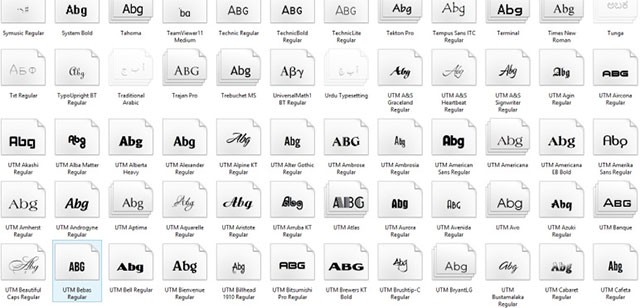
Khám Phá Bộ Font UTM: Giải Pháp Gõ Tiếng Việt Hoàn Hảo
Bộ font UTM, viết tắt của Unicode Thiên Minh, là một tập hợp các font chữ tiếng Việt sở hữu nhiều kiểu dáng độc đáo và ấn tượng.
Với tổng cộng 196 font UTM và 307 font SFU đã được Việt hóa, bộ font này tương thích hoàn toàn với bộ mã Unicode chuẩn.
Điều này đồng nghĩa với việc bạn có thể sử dụng bộ font UTM một cách an tâm trên các phần mềm gõ tiếng Việt phổ biến như Unikey hoặc Vietkey .
Việc tích hợp hoàn hảo với Unicode giúp đảm bảo khả năng hiển thị chính xác và nhất quán của văn bản tiếng Việt trên mọi nền tảng.
Bộ font UTM mang đến sự lựa chọn đa dạng về phong cách chữ, đáp ứng nhu cầu sáng tạo và trình bày văn bản của người dùng.
Tính năng nổi bật của Bộ font UTM
Bộ font UTM được xây dựng để tương thích hoàn toàn với bảng mã Unicode, đảm bảo việc hiển thị và nhập liệu tiếng Việt diễn ra chính xác, loại bỏ hoàn toàn các vấn đề liên quan đến font chữ. Sự tương thích này được kiểm chứng trên các phần mềm gõ tiếng Việt thông dụng như Unikey và Vietkey.
Sự phong phú về kiểu dáng là một điểm mạnh của bộ font này. Nó cung cấp nhiều lựa chọn về phong cách chữ viết, bao gồm cả chữ viết tay, serif, sans-serif, script và display. Điều này cho phép người dùng lựa chọn kiểu chữ phù hợp nhất với mục đích thiết kế, từ những yêu cầu trang trọng đến những sáng tạo độc đáo.
Khả năng tương thích vượt trội
Font UTM có khả năng hoạt động ổn định trên nhiều ứng dụng khác nhau. Từ các phần mềm văn phòng quen thuộc như Microsoft Office, đến các công cụ thiết kế đồ họa chuyên nghiệp như Photoshop, Illustrator, và các ứng dụng giao tiếp phổ biến như Zalo , Skype , Viber .
Ứng dụng đa dạng trong thiết kế
Không chỉ hỗ trợ các font chữ chuẩn tiếng Việt, Bộ font UTM còn sở hữu nhiều mẫu chữ đặc sắc, mang tính nghệ thuật cao, lý tưởng cho việc thiết kế banner, poster phim hoặc tạo chữ trang trí.
Bộ font UTM cung cấp cả nét thanh, nét đậm, đáp ứng nhu cầu sử dụng trong nhiều công việc khác nhau.
Bộ font này bao gồm hàng trăm kiểu chữ đa dạng, từ những kiểu chữ nghiêm trang, hiện đại như UTM Avo, UTM HelvetIns, đến những kiểu chữ nghệ thuật, bay bổng như UTM ThuPhap, UTM Wedding hay UTM Fleur. Mỗi kiểu chữ trong bộ UTM đều được thiết kế tỉ mỉ, hỗ trợ đầy đủ tiếng Việt có dấu, đáp ứng nhu cầu sử dụng trong nhiều lĩnh vực như thiết kế đồ họa, in ấn, quảng cáo và soạn thảo văn bản.